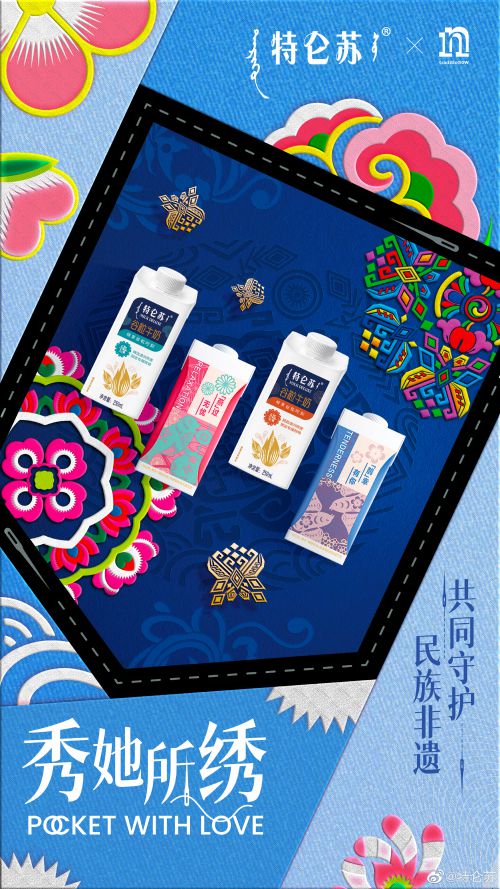
猫啃网风雅宋
风雅宋是一款传承经典韵味的宋体字体,字形方正端庄,重心平稳居中,中宫松紧适中,展现出均衡协调的视觉美感。 风雅宋横画起笔保留传统宋体标志性的三角形装饰,兼具方头笔画的利落与古典纹样的细腻;竖画线条挺括规整,通过适中的笔画粗细对比形成层次分明的视觉节奏。笔画间独立断开的处理,既强化了宋体字的印刷质感,又提升了文本的阅读清晰度。 风雅宋适用于书籍正文、品牌标识、文化宣传等多元场景,在保留传统书法美学的同时,兼顾现代设计的实用性。其典雅稳重的视觉气质,能够为设计作品注入沉静而富有文化底蕴的东方美学韵味。